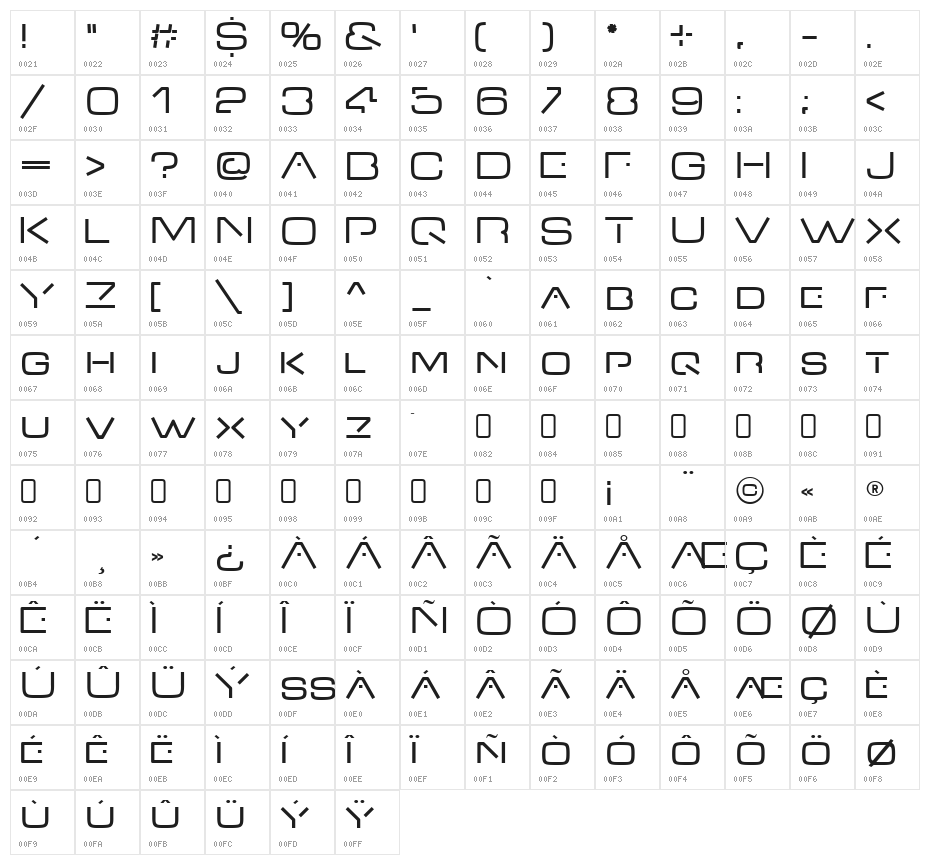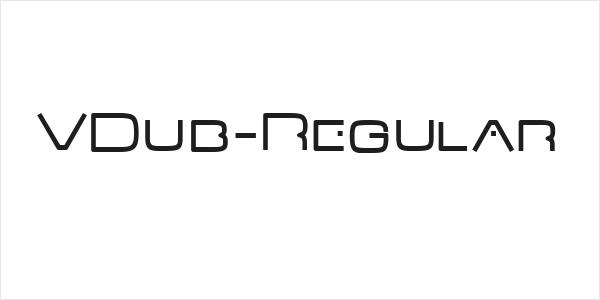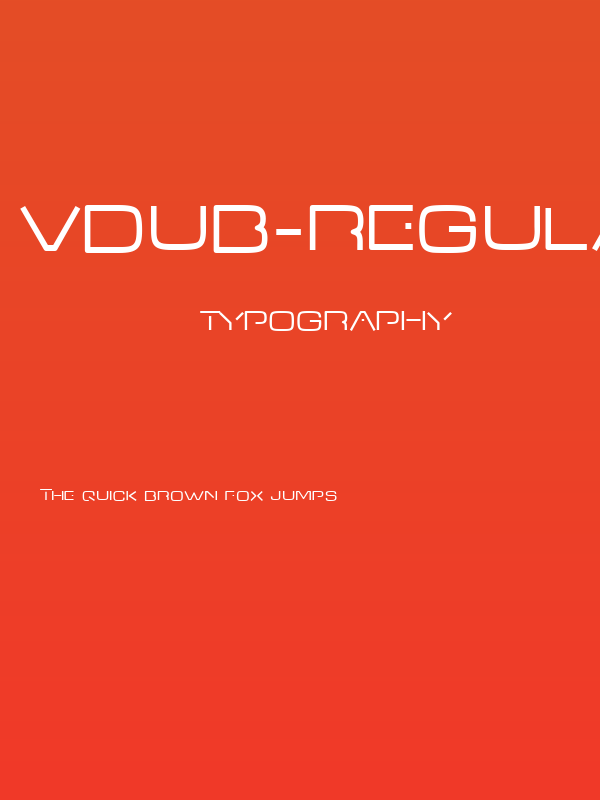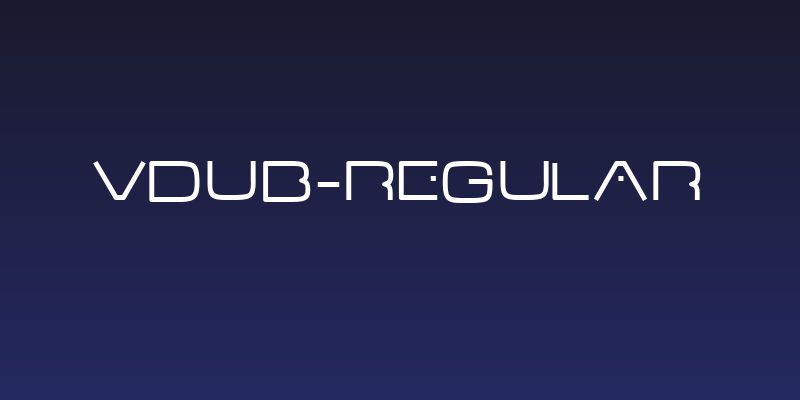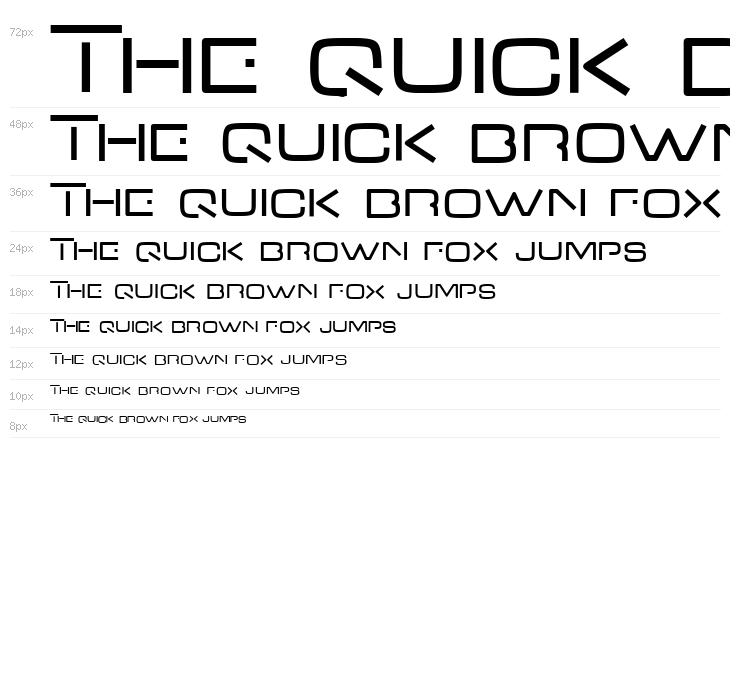
VDub-Regular Font
| Kategorien | Futuristic |
| Anwendungsfall | Headlines, Logos, Digital Interfaces |
| Vorgeschlagene Projekte | Ideal for technology branding, digital interfaces, and modern advertising campaigns. |